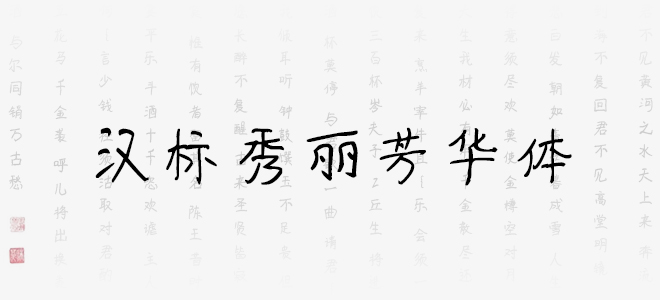
漢標(biāo)秀麗芳華體是一款鋼筆手寫藝術(shù)字體,字體優(yōu)美清新,線條流暢,給人以華麗柔美之感,字體造型生動(dòng)活潑。適用于包裝設(shè)計(jì)、電商、品牌名稱、漫畫、影視綜藝、游戲、各類商業(yè)海報(bào)、戶外廣告標(biāo)題等設(shè)計(jì)領(lǐng)域。
漢標(biāo)秀麗芳華體